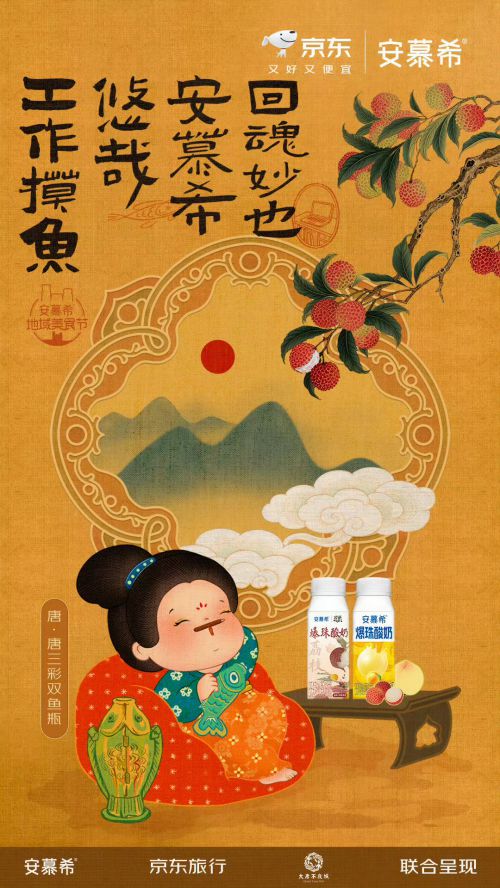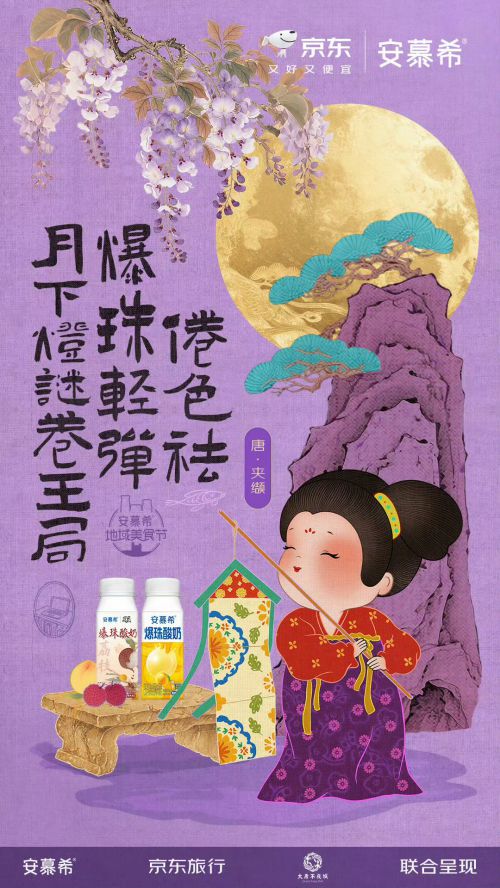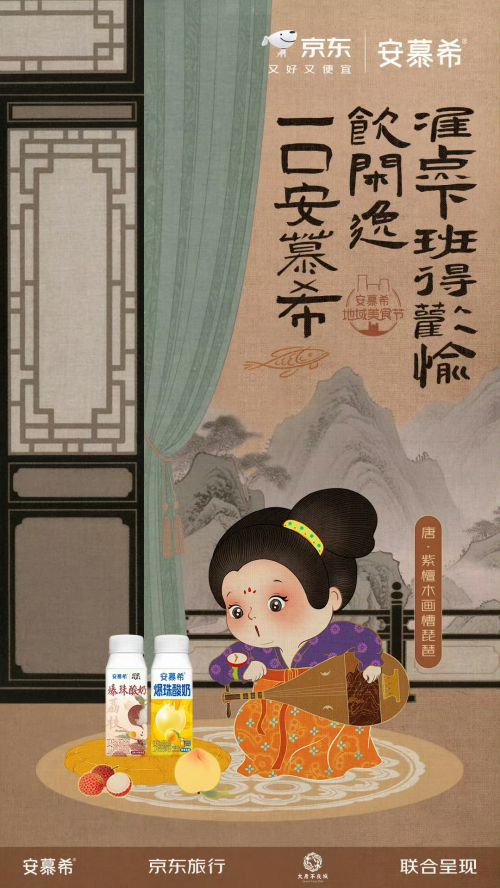
演示佛系体
佛系体是一款自带禅意气质的特色创意字体,以扁宽舒展的字形结构传递从容自在的视觉语言。字体采用居中重心设计,配合宽博中宫,让整体形态稳重大气又不失舒展;笔型融入柔和圆角与圆润笔触,粗实均匀的线条既保留饱满力量感,又通过圆头笔画增添亲和温度。独特的笔画断开处理是其点睛之笔,在连贯的视觉节奏中留出巧妙呼吸空间,打破沉闷的同时更显灵动层次。无论是文化主题海报、生活美学设计,还是佛系风格文创作品,佛系体都能以“圆融包容”的字形气质与“断而不离”的笔触韵律,为内容注入宁静而富有生命力的视觉魅力,成为传递平和心境的理想字体选择。